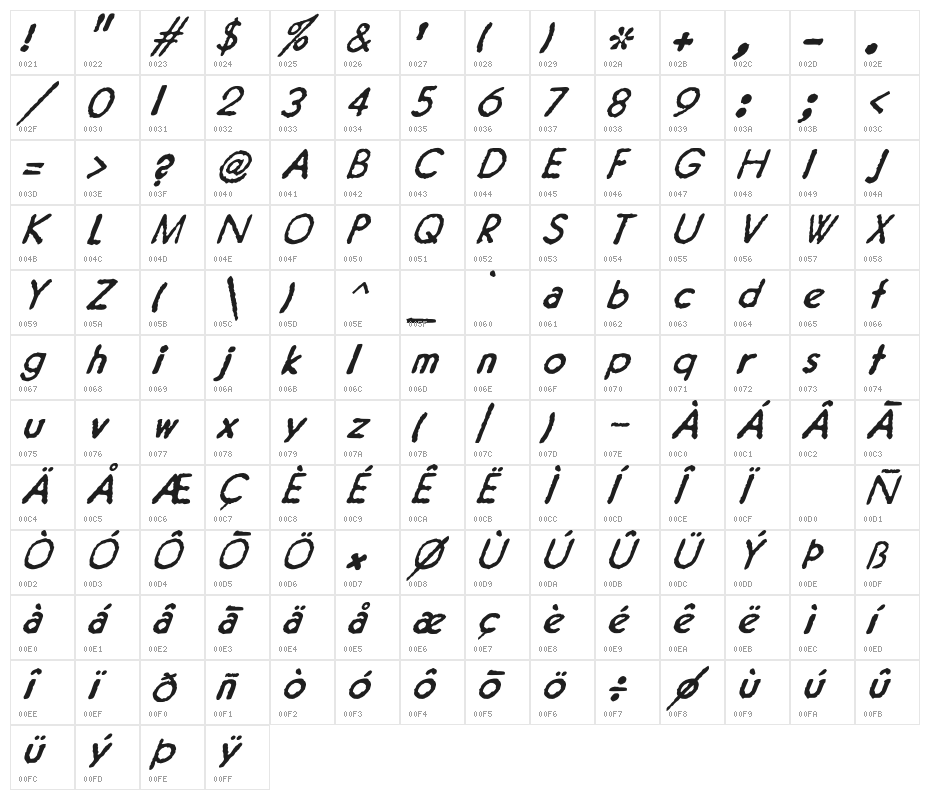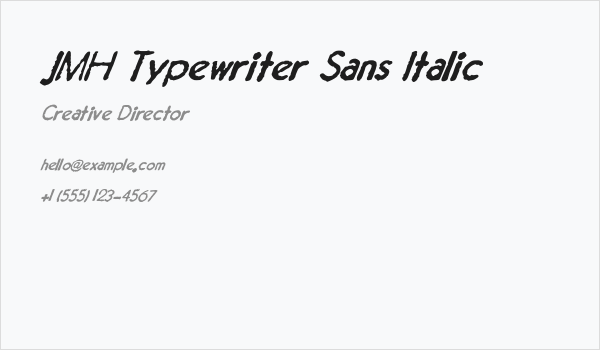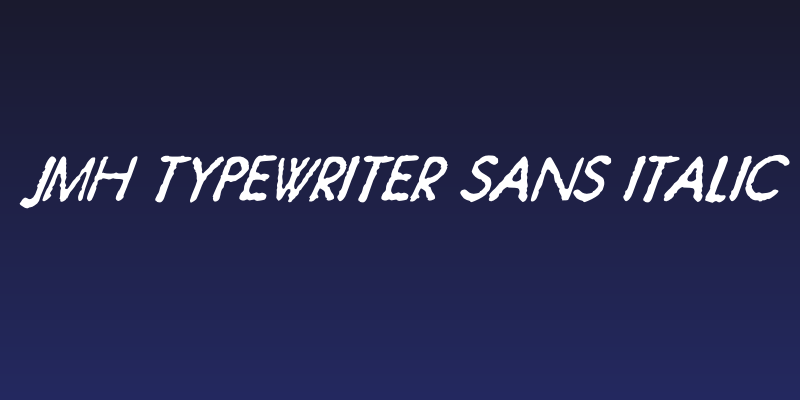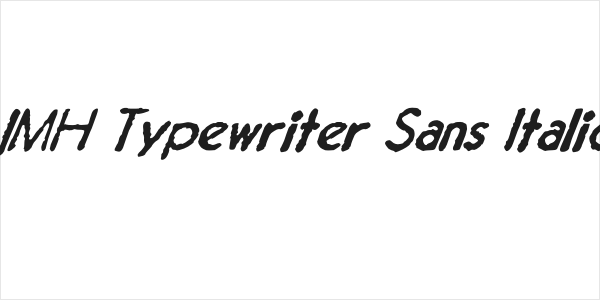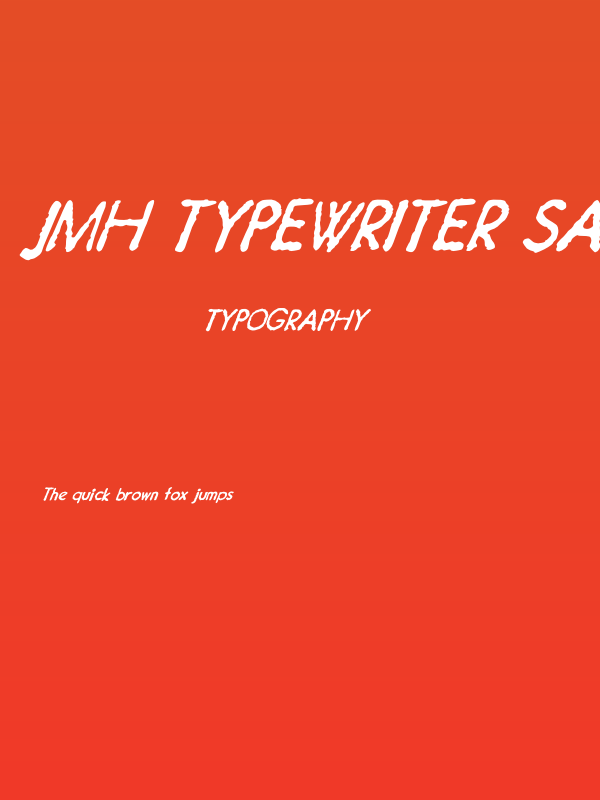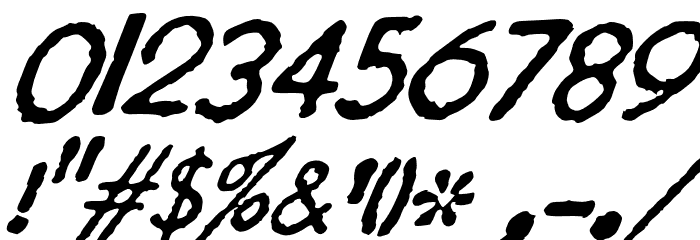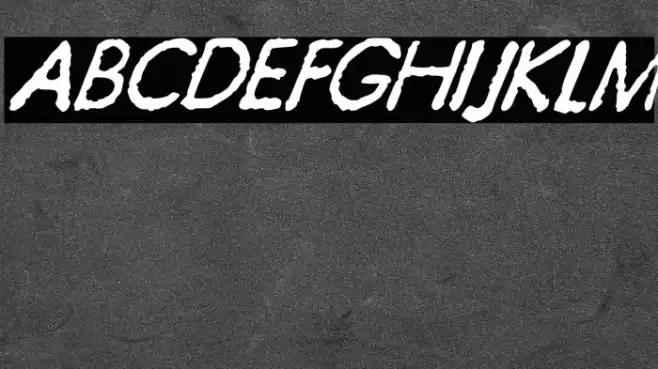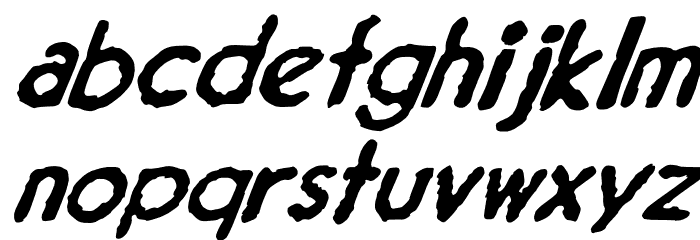
JMH Typewriter Sans Italic Font
| Gesamtstil | Vintage |
| Anwendungsfall | Logos, Headlines, Invitations |
| Vorgeschlagene Projekte | Ideal for retro-themed designs, personal notes, invitations, and branding that requires a nostalgic touch. |